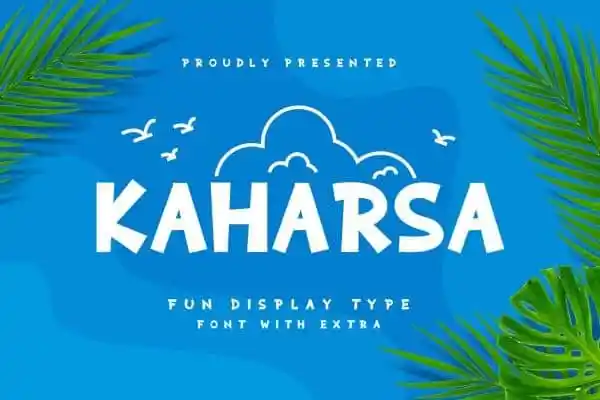
Kaharsa Display Font – Download Grátis
A Kaharsa Display Font é uma escolha perfeita para qualquer projeto criativo que exige charme e simplicidade. Inspirada no estilo do pop art e nos desenhos animados, ela oferece um visual descontraído e alegre, ideal para criar design infantil ou projetos divertidos. Com linhas retas e uma forte identidade visual, esta fonte se destaca em qualquer aplicação gráfica: desde a criação de logomarcas até a desenvolvimento de embalagens, cartazes, cabeçalhos e arte do painel da sua padaria; passando por desenhos para camisetas ou design de propaganda. Além disso, é uma fonte ótima para criar conteúdo para mídias sociais e produtos infantis como canecas e bandeiras para festivais de café. É a escolha perfeita tanto para projetos pessoais quanto comerciais, tornando-a um recurso indispensável para qualquer designer que busca novas maneiras criativas de expressar sua visão.